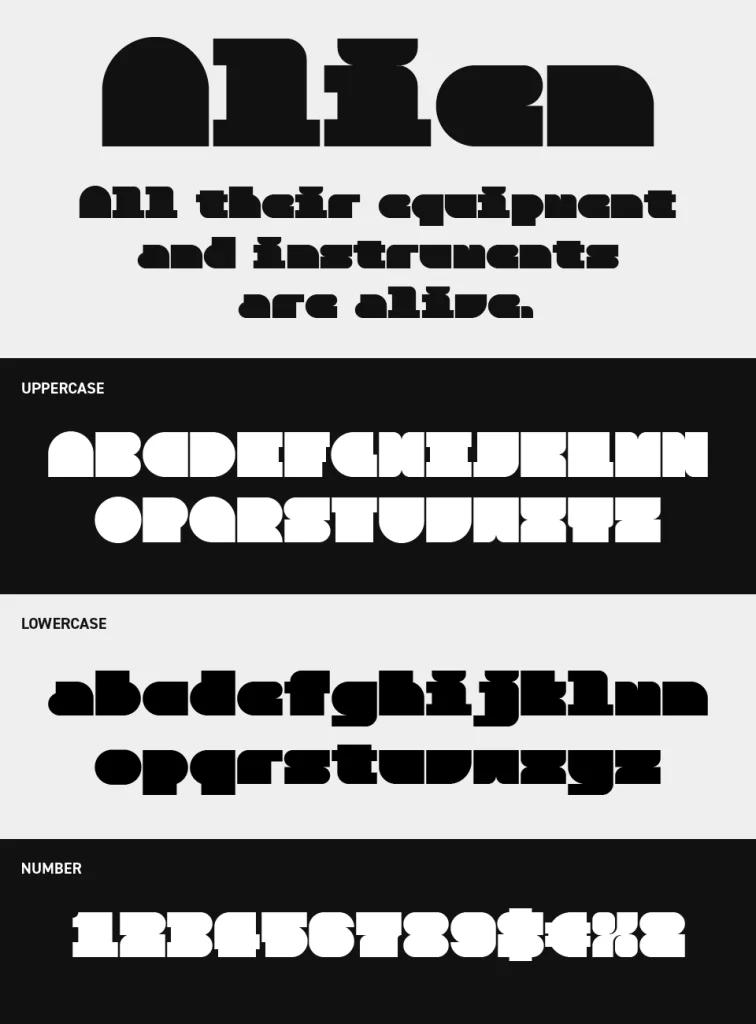
Alien Block Font
Alien Blockフォントは、幾何学的なブロックを組み合わせたような構造が特徴的な、無機質で近未来感のあるディスプレイフォントです。
直線的で極太フォルムが強い存在感を放ち、どこかレトロフューチャーな空気感も感じさせます。
文字の窓が塗りつぶされているので、判読性は低いディスプレイフォントですが、独特の設計によって、単なる可読性以上にグラフィックとしての面白さを持っています。ゲームロゴ、近未来UI、デジタルカルチャー、実験的なポスターなど、ビジュアルそのものに個性を与えたい場面で活躍するフォントです。